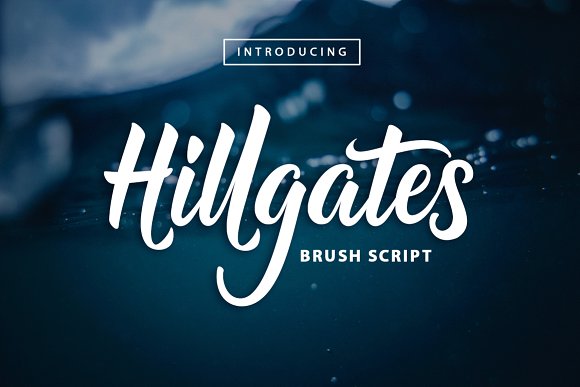
Hillgates Font
Hillgates Font – الأناقة الكلاسيكية بروح عصرية
اكتشف Hillgates Font، الخط المثالي الذي يجمع بين الفخامة والطابع الكلاسيكي بأسلوب عصري فريد. يتميز هذا الخط بتصميمه الأنيق والمتوازن، مما يجعله خيارًا مثاليًا لمجموعة واسعة من المشاريع، بما في ذلك:
بفضل تفاصيله الدقيقة وانسيابيته الفريدة، يضفي Hillgates Font لمسة من التميز على أي تصميم، مما يساعدك على إيصال رسالتك بأسلوب أنيق وجذاب. اجعل إبداعك يتألق مع هذا الخط الاستثنائي!